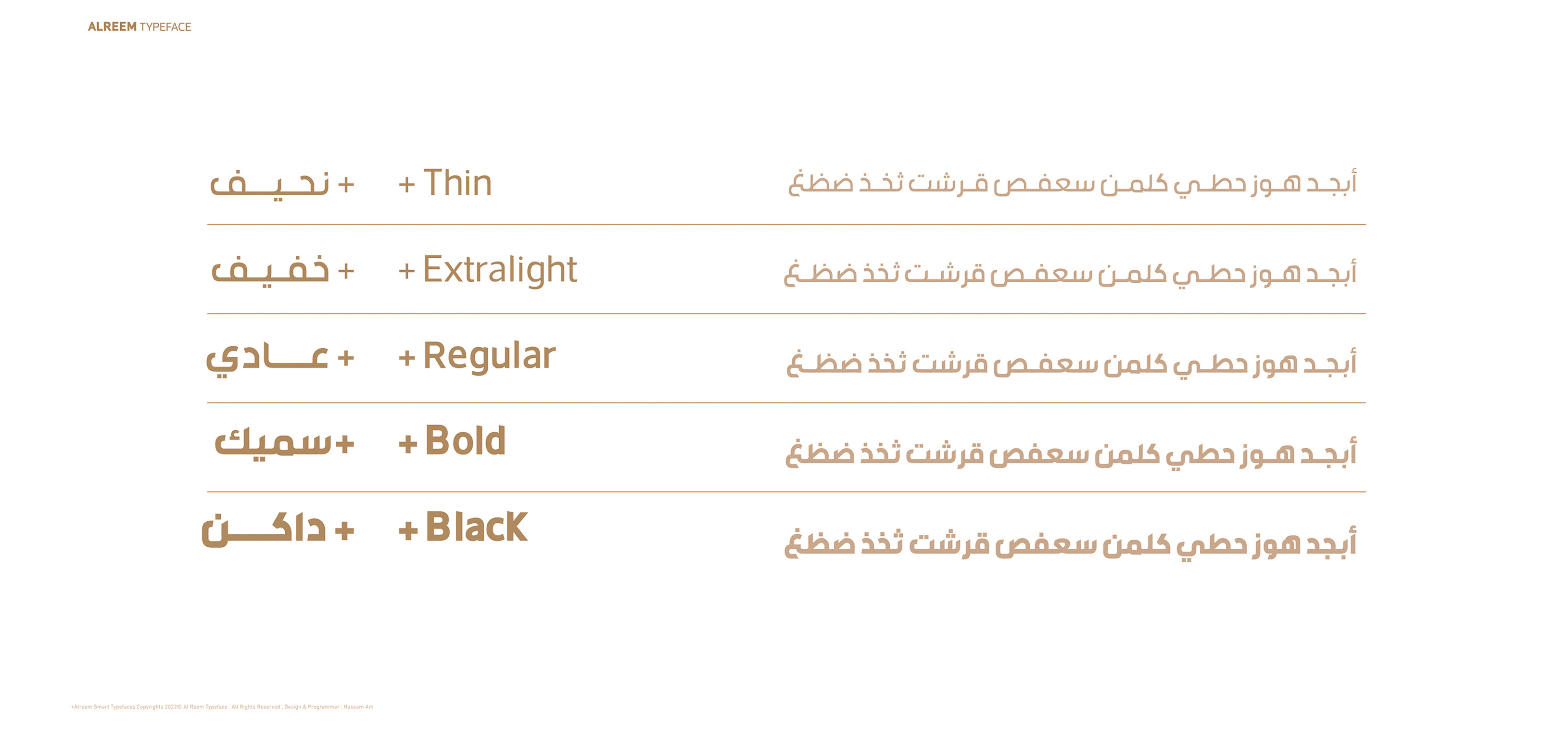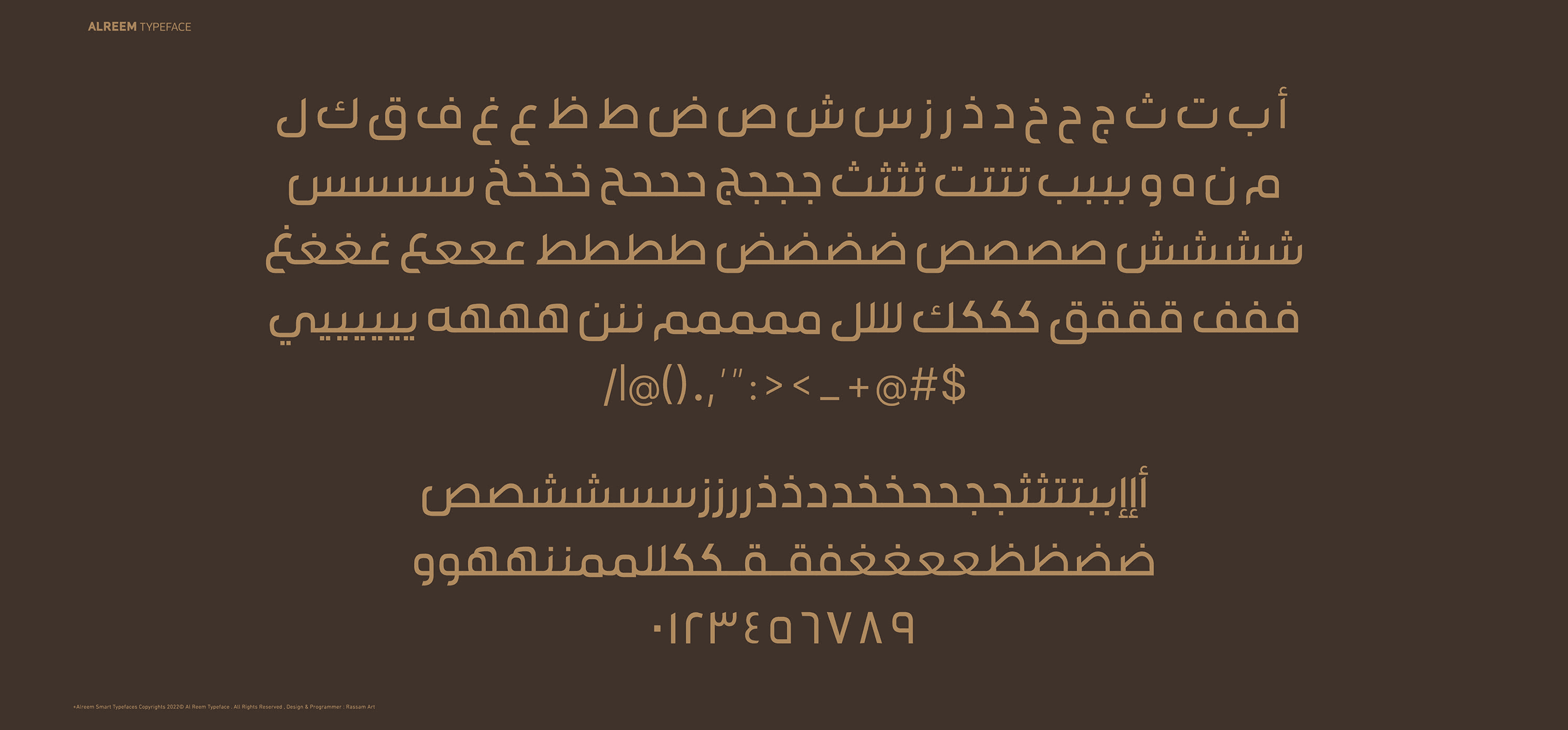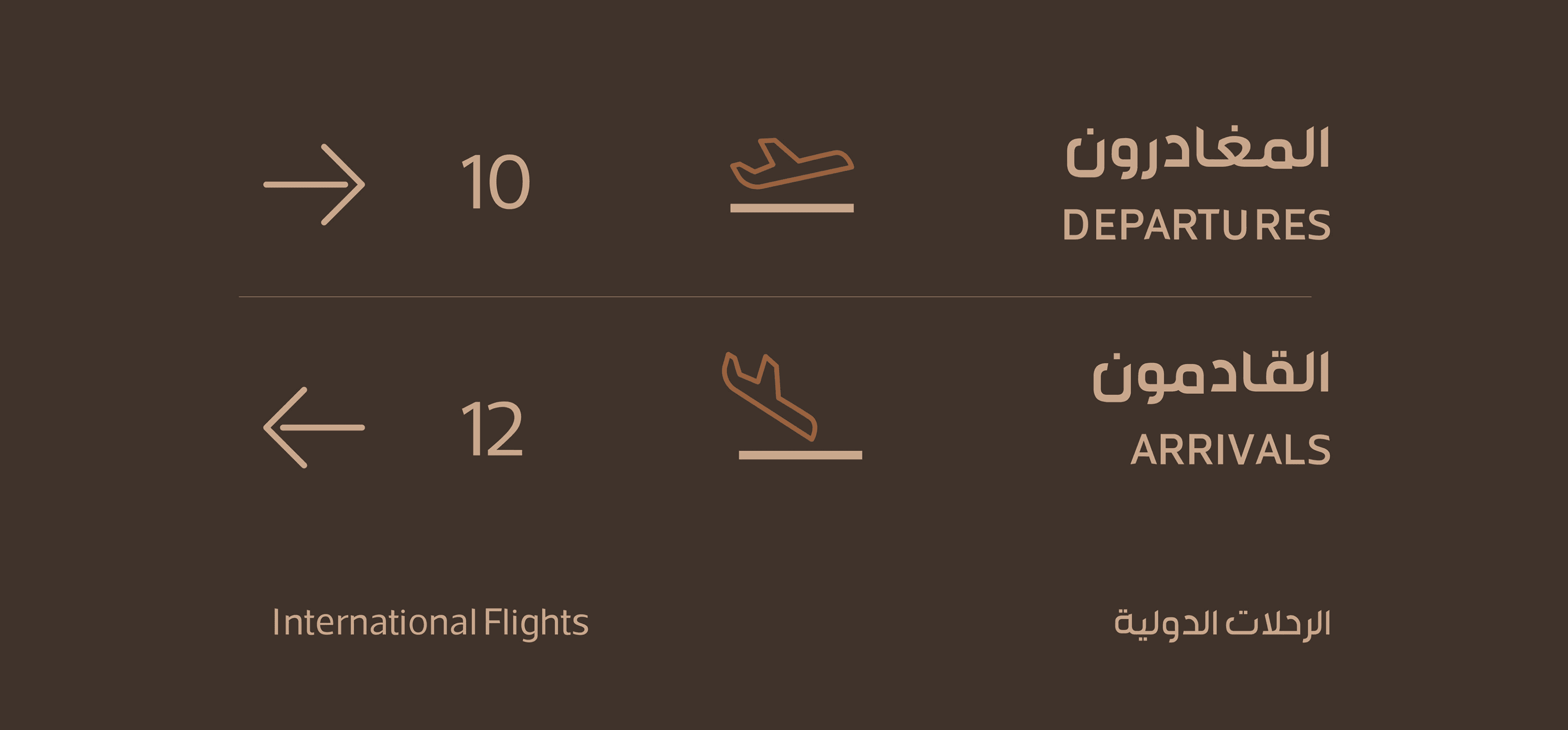
خط الريم – ALREEM Typeface
خط عصري يتميّز بتصميم قوي وواضح، يتكوّن من 5 أوزان مختلفة، مما يمنحه مرونة كبيرة في الاستخدامات المتعددة.
يدعم الخط اللغتين العربية واللاتينية، ما يجعله مناسبًا للتصميمات ثنائية اللغة، سواء للعناوين الجريئة أو النصوص الرسمية.